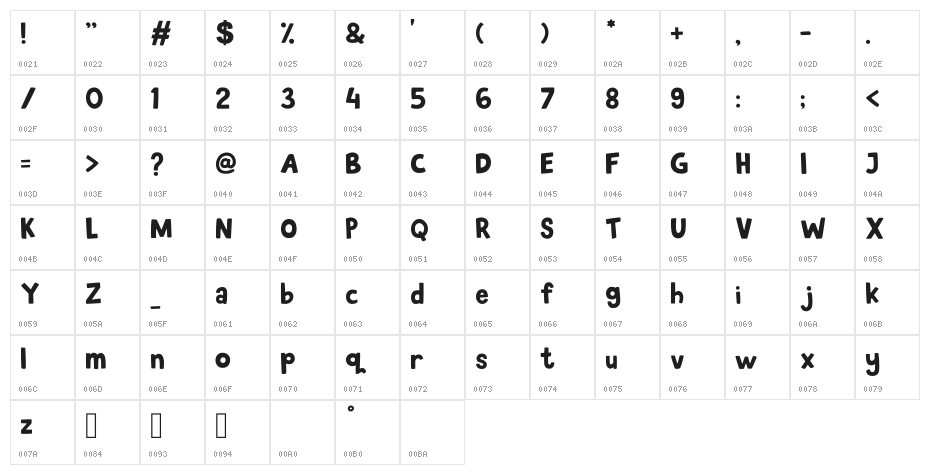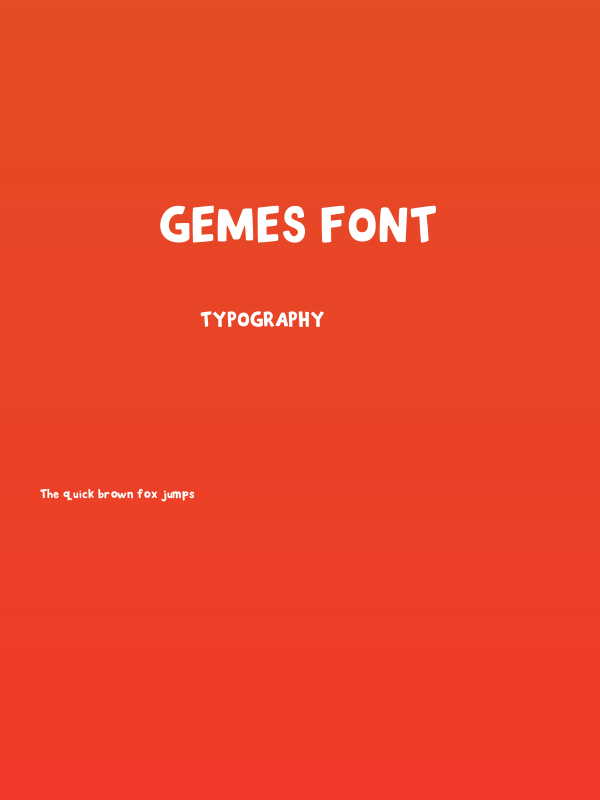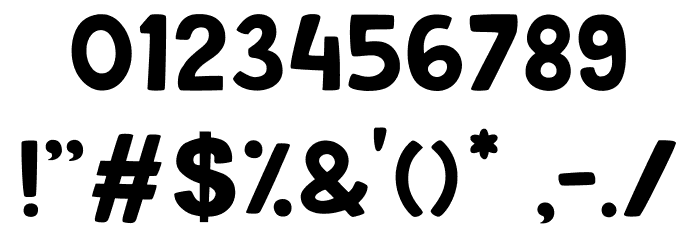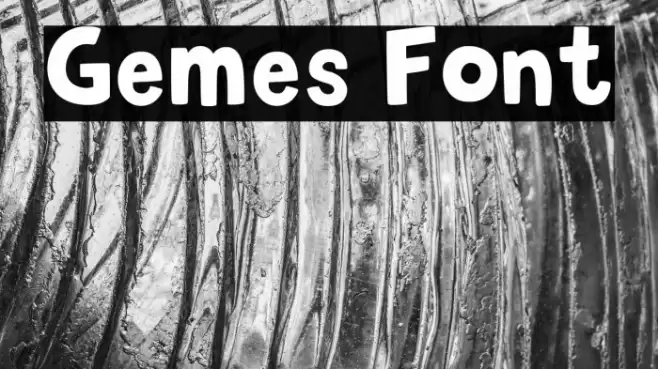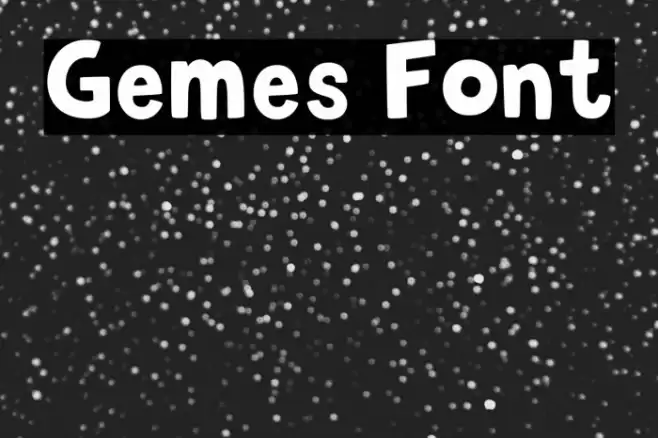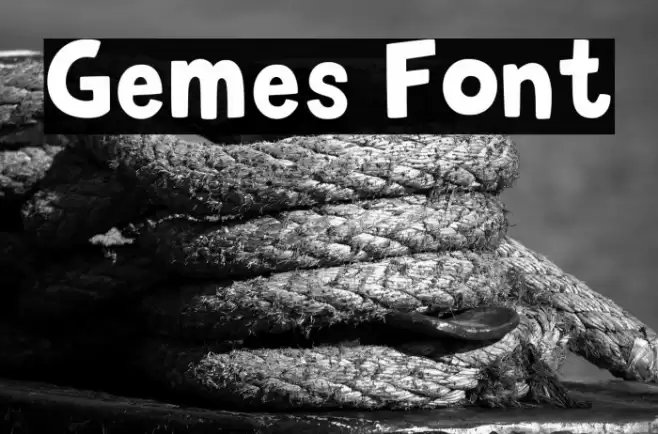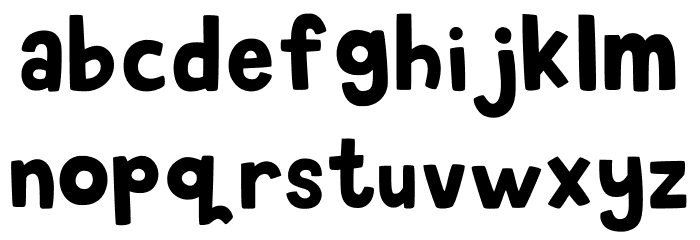
Gemes Font Font
| Stile generale | Playful, Whimsical |
| Progetti proposti | Ideal for children's books, playful branding, posters, and social media graphics. |